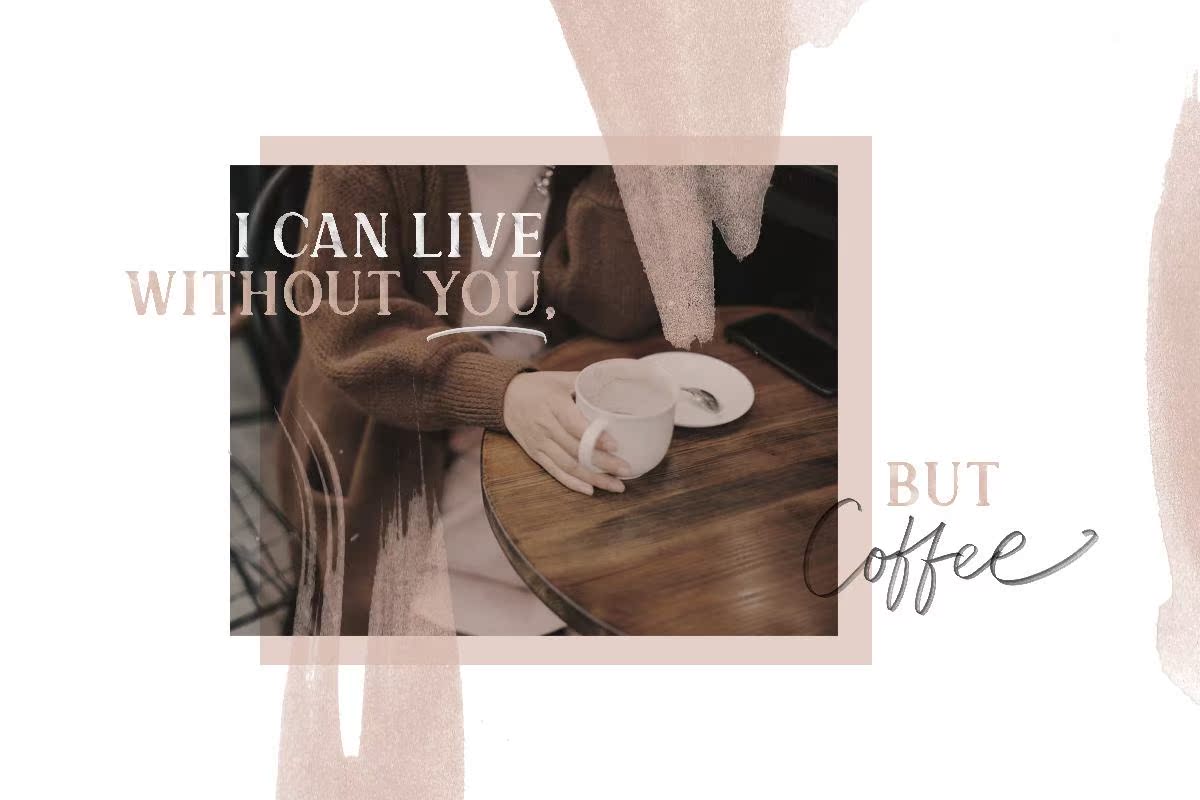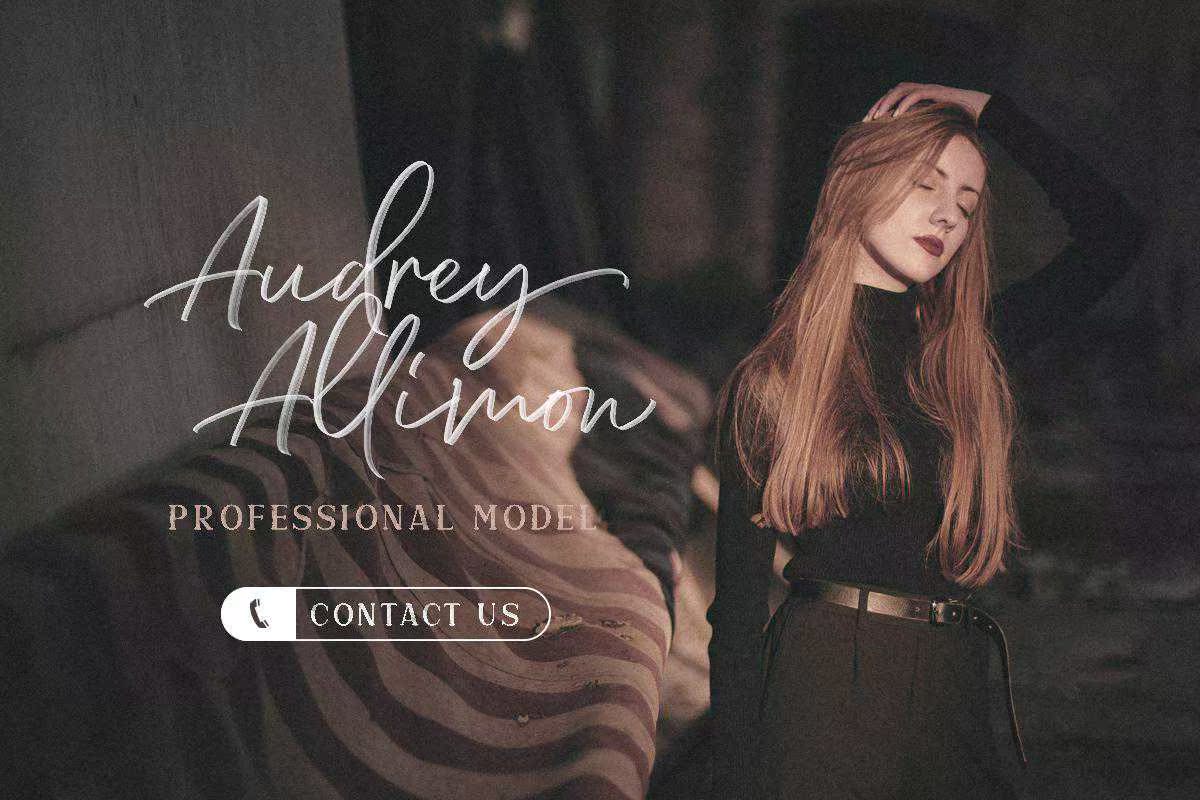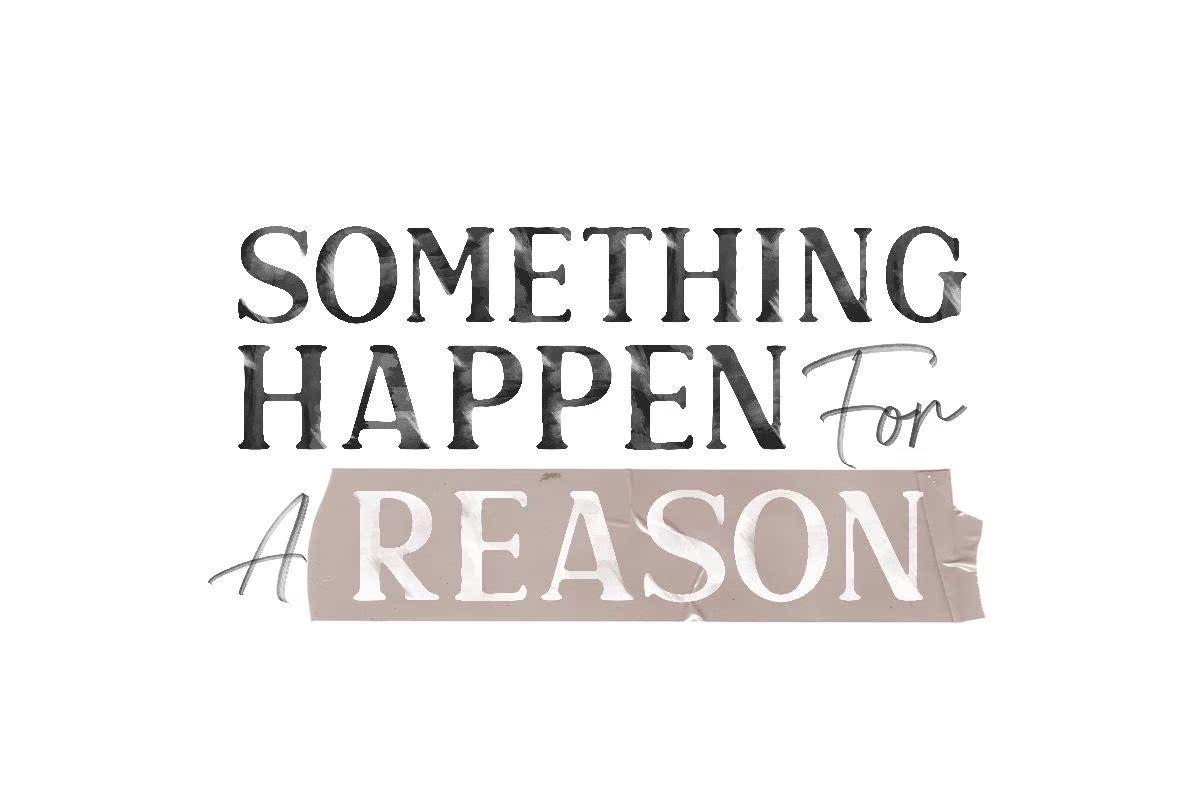
DianaWebbrisaDisplayTypeFaceFamilywhichhastwofonthatsavgscript和svgserfi!Whataperfectpair。该文本使其看起来像自然笔迹。非常适合需要字体的用户,如标题、标识、服装、邀请、品牌、包装、广告等。该字体包括大写、小写、标点符号、符号和数字、文体设置、替换、连字、,ETCALSO支持多语言和ReadyPuaEncoded.DianaWebbrisaDisplayTypeFaceFamily,它的字体为SvgScript和SvgSerfi!WhattaperFectPair。该文本使其看起来像自然手写。非常适合您需要标题、标识、服装、邀请、品牌、包装、广告等字体的用户。该字体包括大写、小写、标点符号、符号和数字、样式设置交替、连字等,支持多语言和ReadyPuaEncoded。